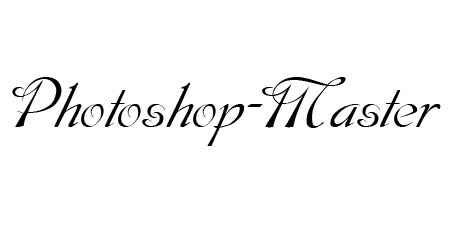
Дополнения Шрифты Татьяна Гапонова 1 августа 2009 Шрифт - DOBKIN Plain Красивый шрифт без поддержки русского языка. Скачать Шрифт - DOBKIN Plain
красивый!
Превосходный шрифт!
хороший шрифт